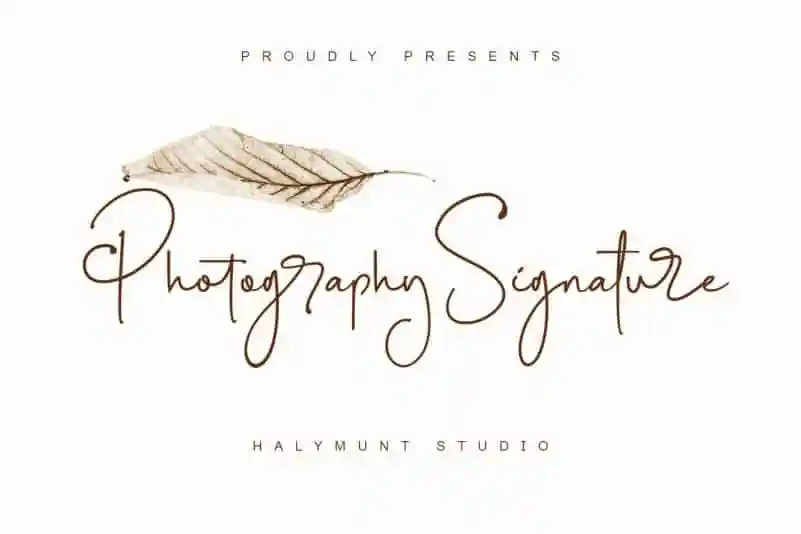
Photography Signature Script Font – Download Grátis
A Photography Signature Script Font é perfeita para quem quer dar vida a seu projeto com um estilo elegante e artesanal. Ela traz uma assinatura única com letras decorativas, criando um toque único que se destaca em qualquer aplicação – seja para criação de logotipos de estilo de assinatura, promoção de blogs ou websites, ou até mesmo cartões de visita e cartas devidamente personalizados. Com sua linha dinâmica que parece dançar, essa fonte é ideal para criar um visual único e memorável em qualquer projeto. É uma opção perfeita para quem busca um toque especial que transmite sofisticação e individualidade ao mesmo tempo. Criada pelo excelente talento da Halymunt Studio, esta fonte é a escolha ideal se você está buscando adicionar um toque autêntico e único em suas criações digitais.